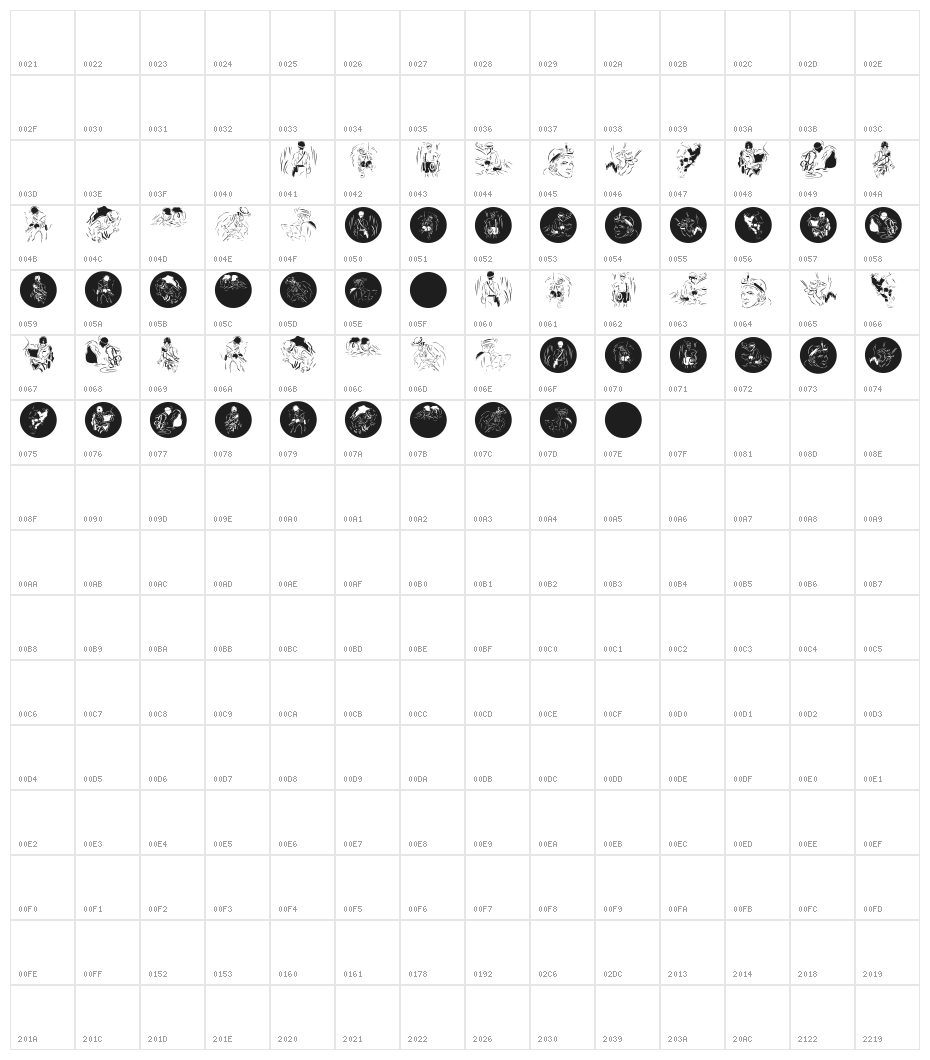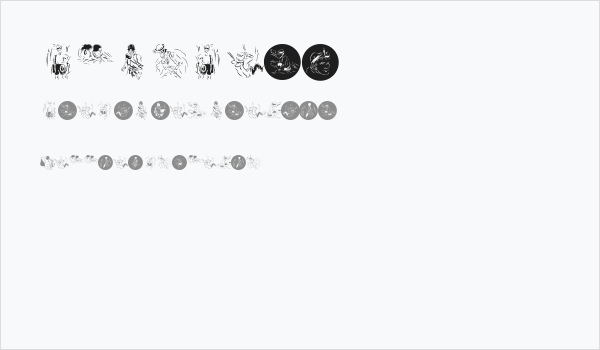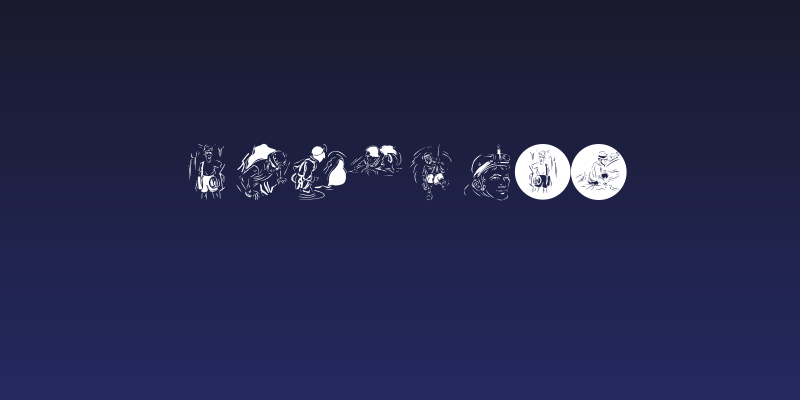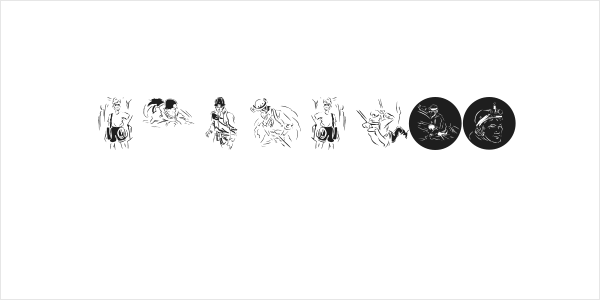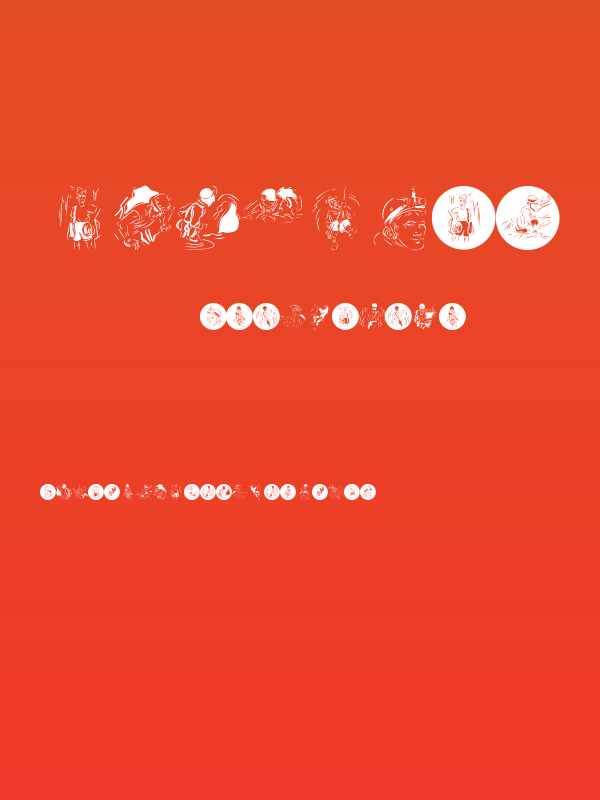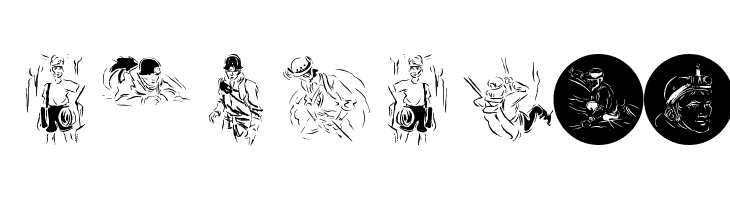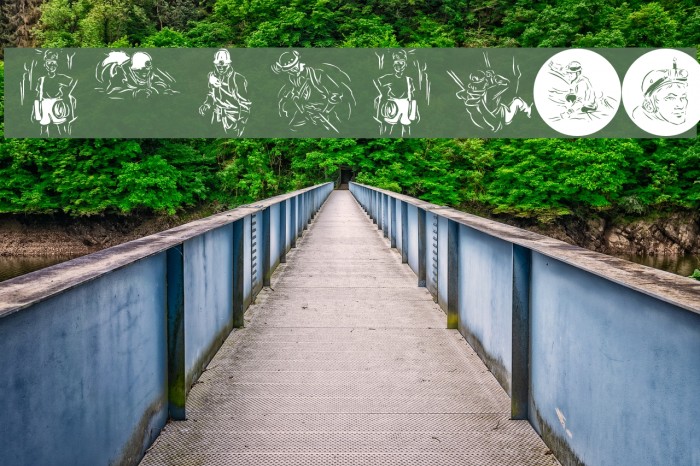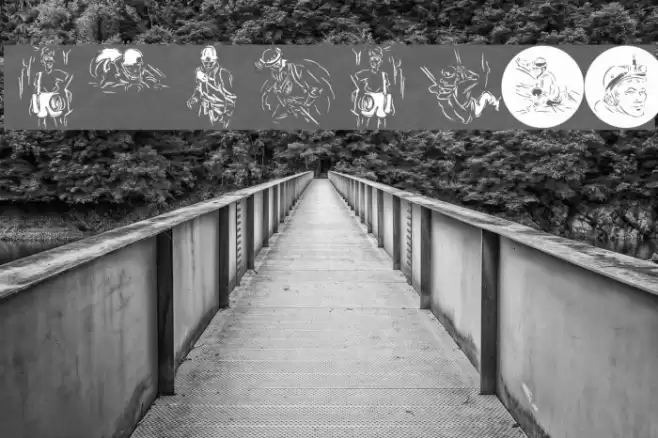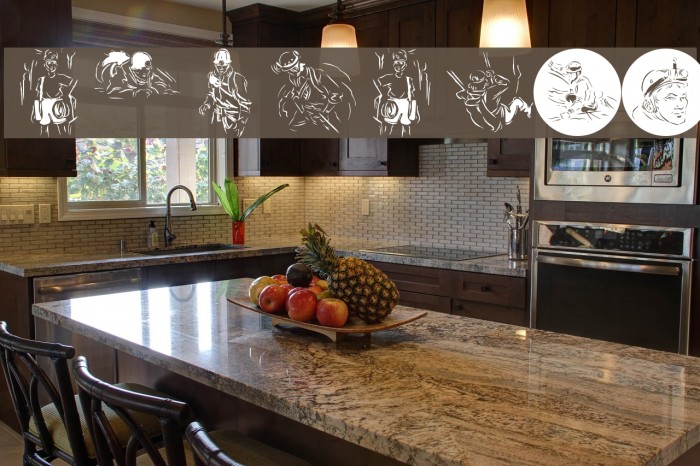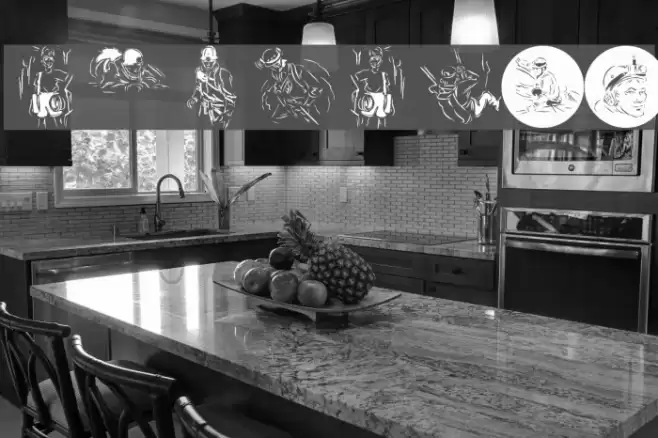
Climbers2005 Font
| Stile generale | Decorative, Illustrative, Thematic |
| Caso d'uso | Logos, Posters, Themed graphics, Event materials |
| Progetti proposti | Outdoor adventure branding, climbing gym posters, event flyers, themed merchandise, educational materials about mountaineering. |